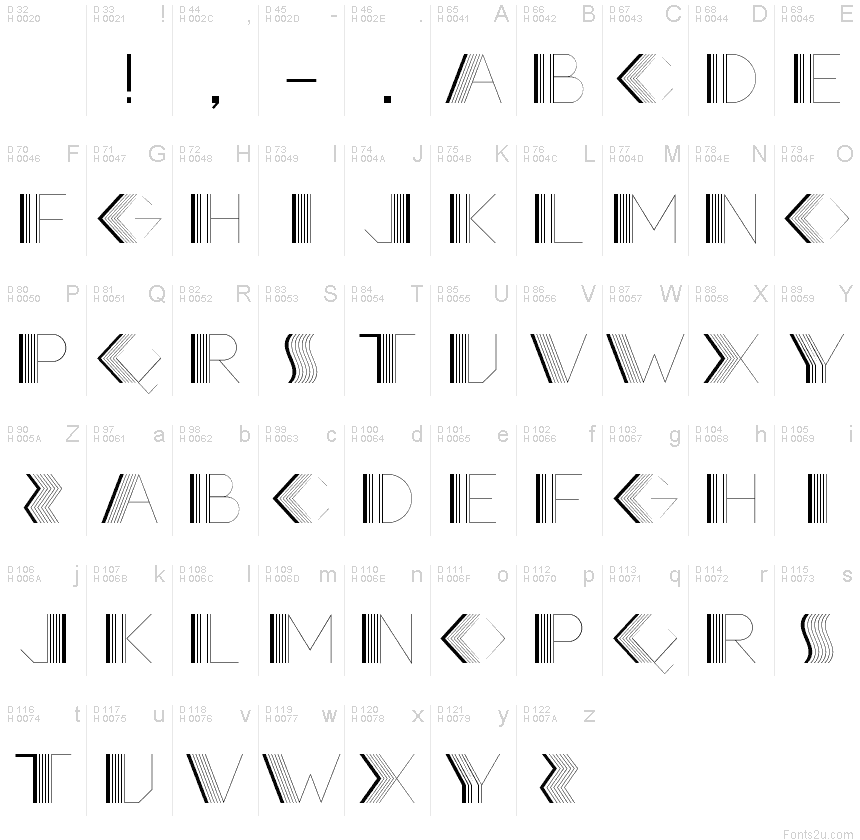
Kaviva to darmowy, retro font display typu inline, zbudowany z wysokich, geometrycznych wielkich liter i powtarzających się cienkich linii. Otwarta forma liter balansuje między ostrymi przekątnymi a blisko osadzonymi równoległymi liniami, tworząc architektoniczny rytm, który przywodzi na myśl eksperymentalne liternictwo z plakatów lat 70. i precyzyjne projekty graficzne.
Użyj tego darmowego fontu w plakatach muzycznych, identyfikacjach festiwalowych, okładkach magazynów czy lookbookach modowych – wszędzie tam, gdzie typografia ma być równie ważnym elementem obrazu, co przekazu. Sprawdzi się także w krótkich nagłówkach i wielkoformatowych monogramach, gdzie hojne proporcje pozwalają na wyeksponowanie pasiastej konstrukcji, tworząc odważny, uporządkowany wzór.